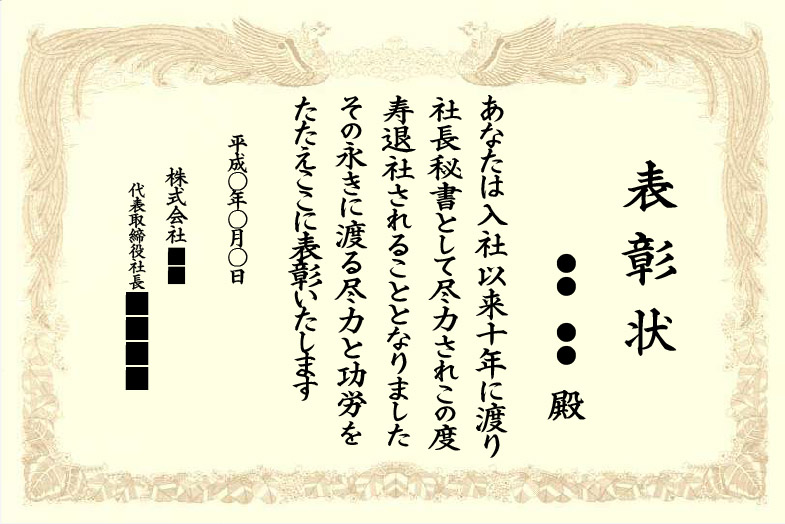
白洲書状書体はなぜ手書きと勘違いするのか
白洲賞状フォンはいろんな線の太さが用意されています。
- ・NSK白洲賞状フォント ( W0, W1, W2, W3, W4, W5 )
- ・NSK白洲学校賞状フォント ( W0, W1, W2, W3, W4, W5 )
- ・NSK白洲賞状表題フォント ( W1, W2, W3, W4, W5 )
- ・NSK白洲賞状フォント/縦縮小 ( W1, W2, W3, W4, W5 )
- ・NSK白洲賞状フォント/横縮小 ( W1, W2, W3, W4, W5 )
以下に作成見本をご案内します
手書きではありません、NSK白洲書状専用フォントで作成しました。